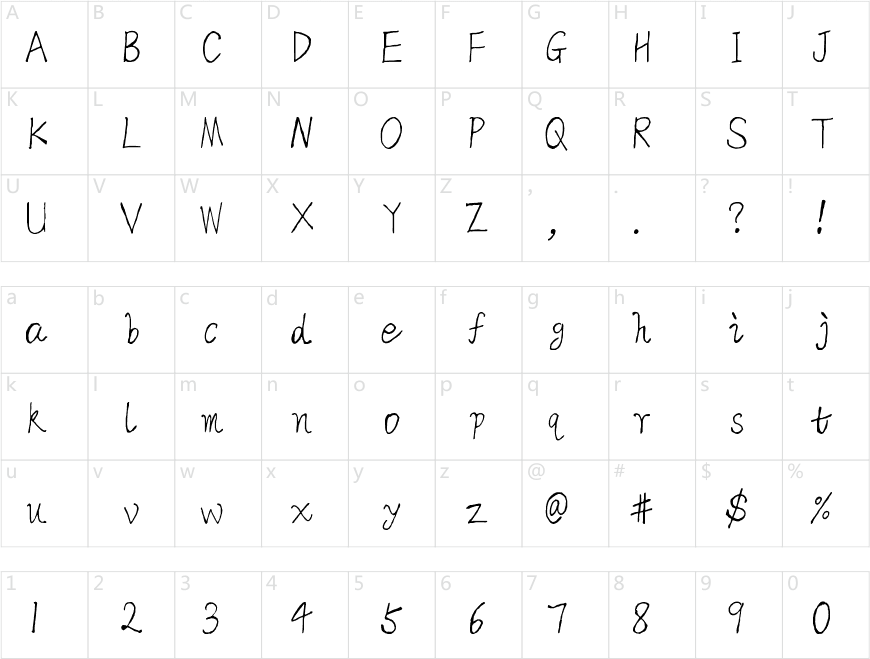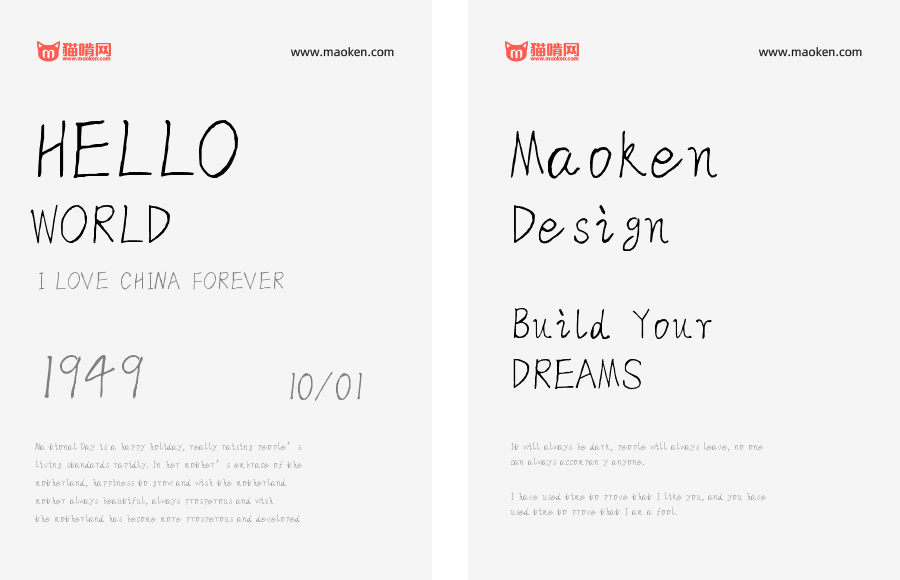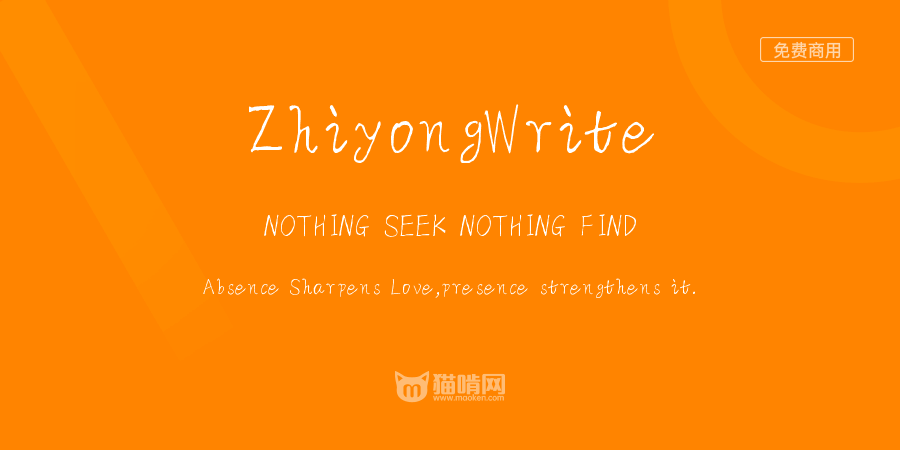
ZhiyongWrite
Diligence climbs; perseverance sails.
ZhiyongWrite NOTHING SEEK NOTHING FIND Absence Sharpens Love, presence strengthens it.
ZhiyongWrite(智勇手书英文体)
适于作为英文正文字体使用。
可与之前的免费字体手书体,搭配使用。